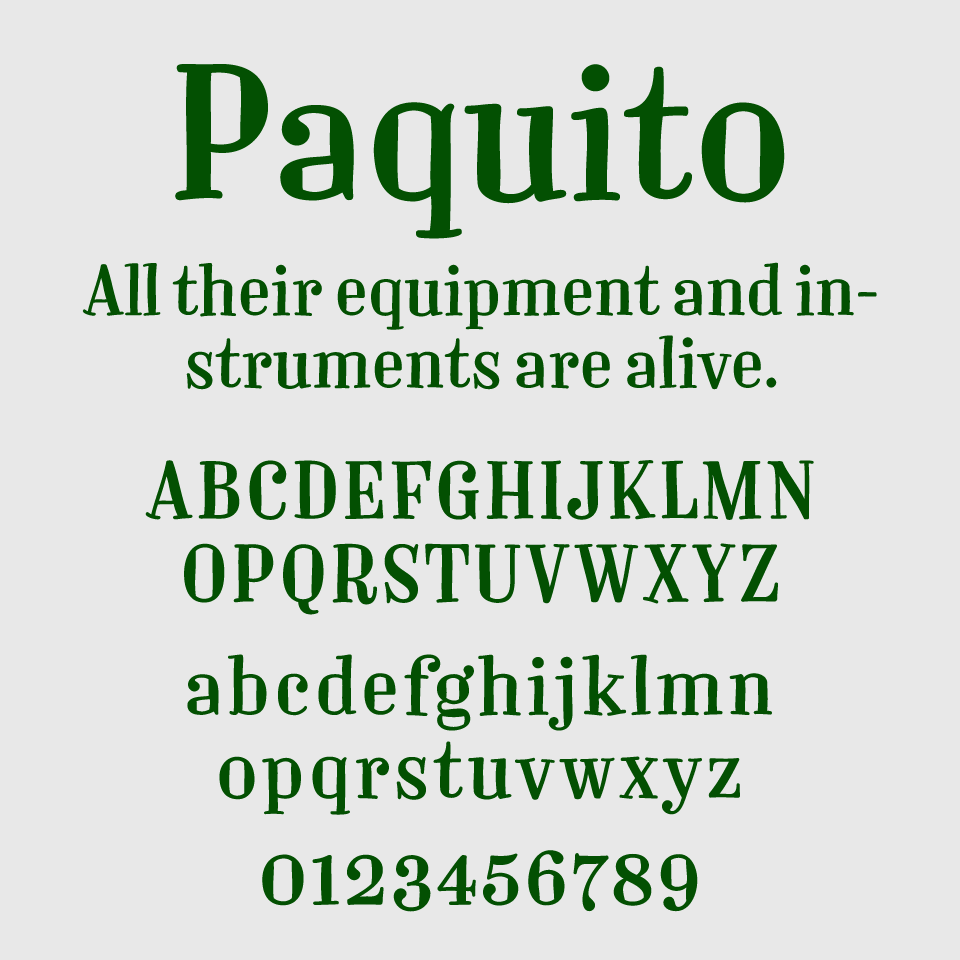
Paquitoフォントは、細部に揺らぎを持たせたような手書き感のあるアウトラインが特徴のセリフ体です。
柔らかなセリフと縦に長いプロポーションが、どこか素朴で親しみやすい印象を与えます。手書き風のラフさと活版印刷のような味わいを併せ持っています。
フォーマルすぎず、それでいて品のある佇まいは、ナチュラル系ブランドのロゴや雑誌の見出し、クラフト感のあるデザインとぴったりです。